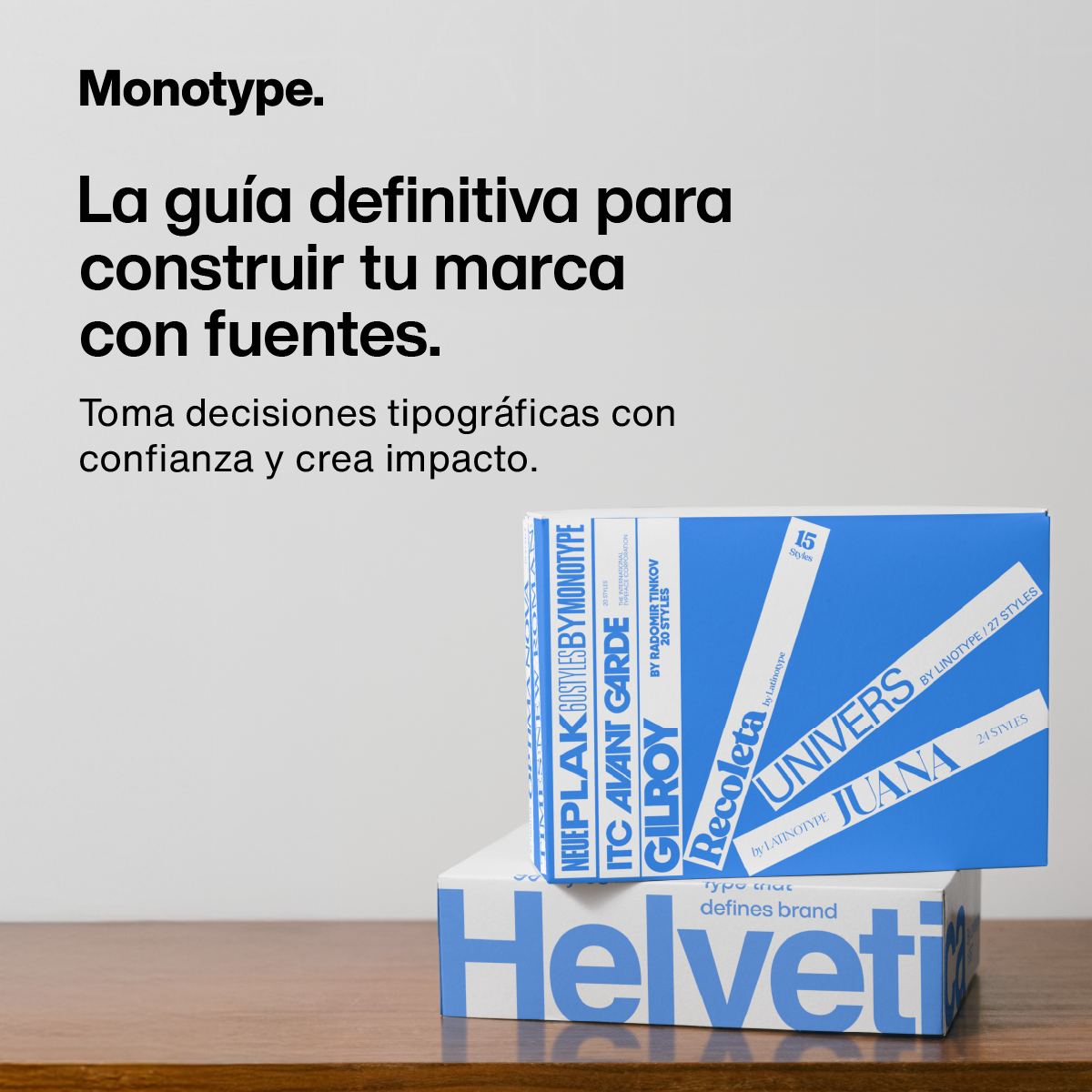
eBook: La guía definitiva para construir tu marca con fuentes.
Descubre cómo la tipografía puede transformar tu marca. Sumérgete en el papel fundamental que desempeñan las fuentes a la hora de dar forma a la identidad de una marca, reforzar las conexiones emocionales y crear historias que enganchen. Desde la selección de tipografías personalizadas hasta el mantenimiento de la coherencia en todas las plataformas, este eBook ofrece consejos prácticos para elevar la presencia de tu marca en un entorno cada vez más competitivo.
Aspectos destacados del contenido de la guía:
- La importancia de las fuentes personalizadas para reflejar los valores y la personalidad de la marca.
- Cómo una tipografía coherente refuerza el reconocimiento de marca en todos los puntos de contacto.
- Formas en las que las fuentes pueden modernizar tu marca sin perder su esencia.
- El impacto emocional de la tipografía en la construcción de confianza y cercanía con tu audiencia.